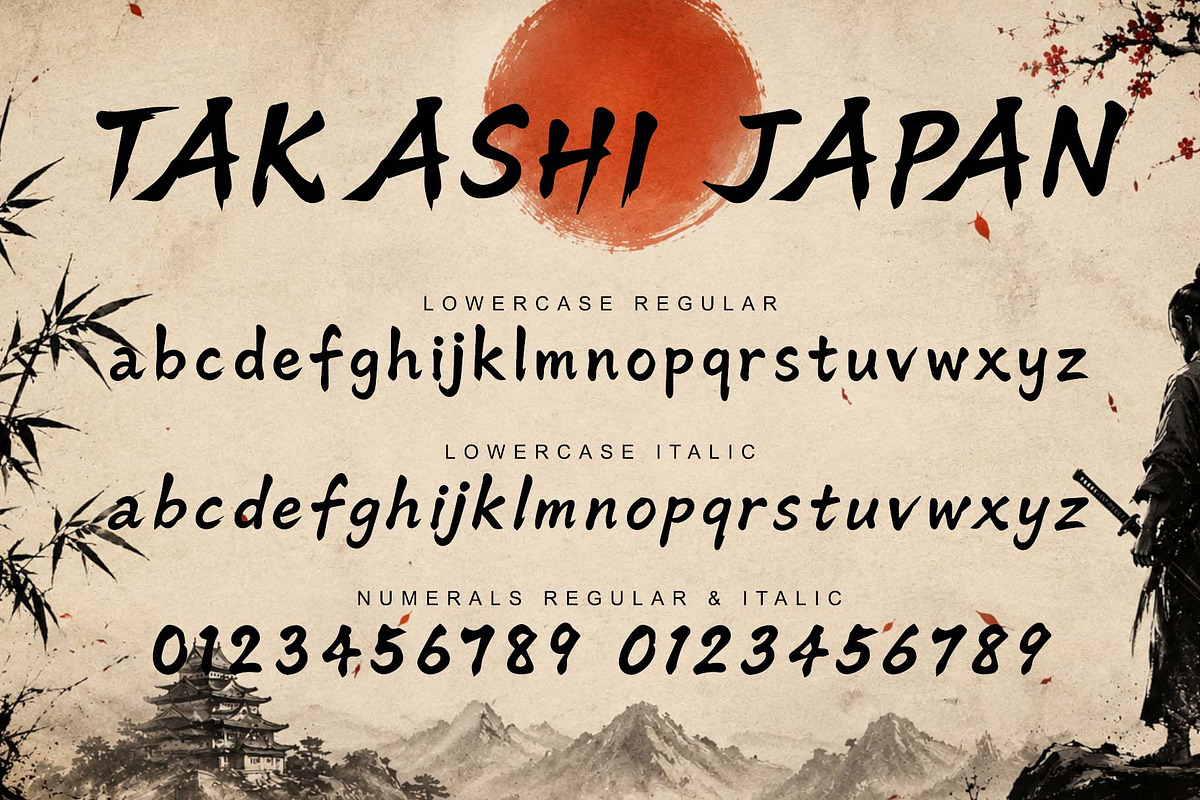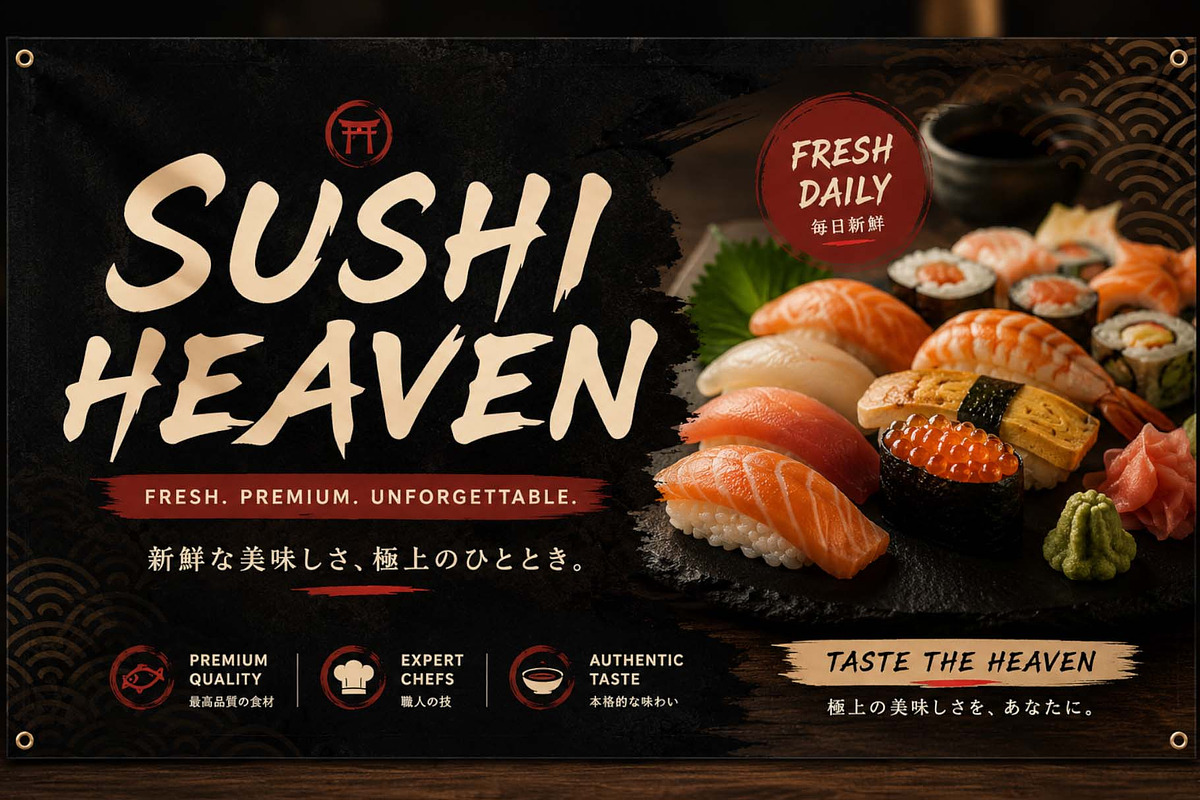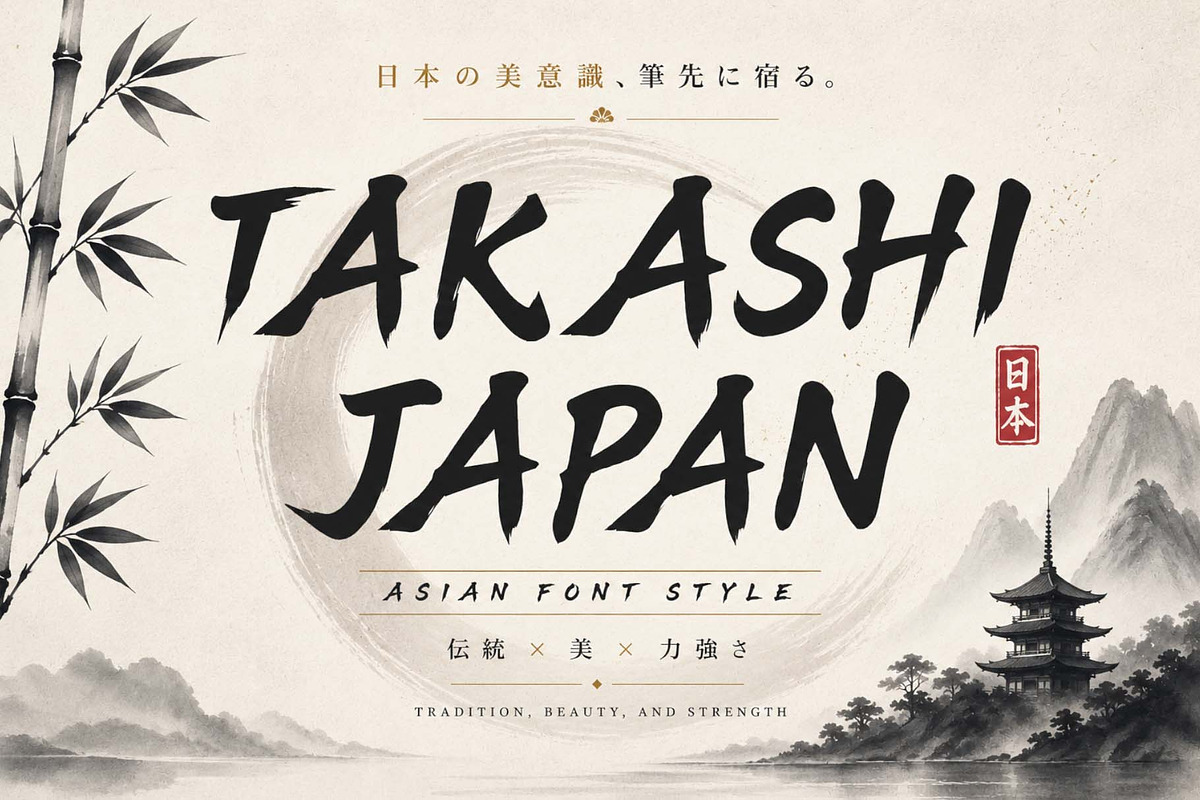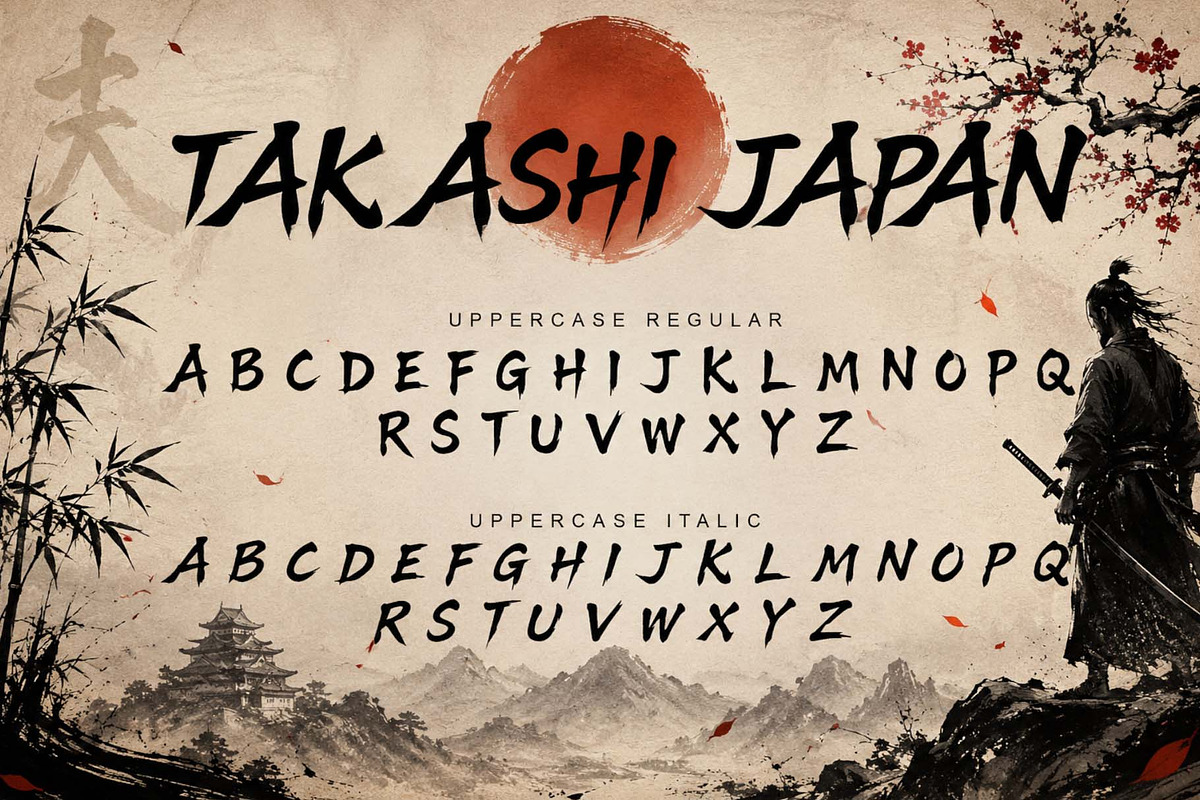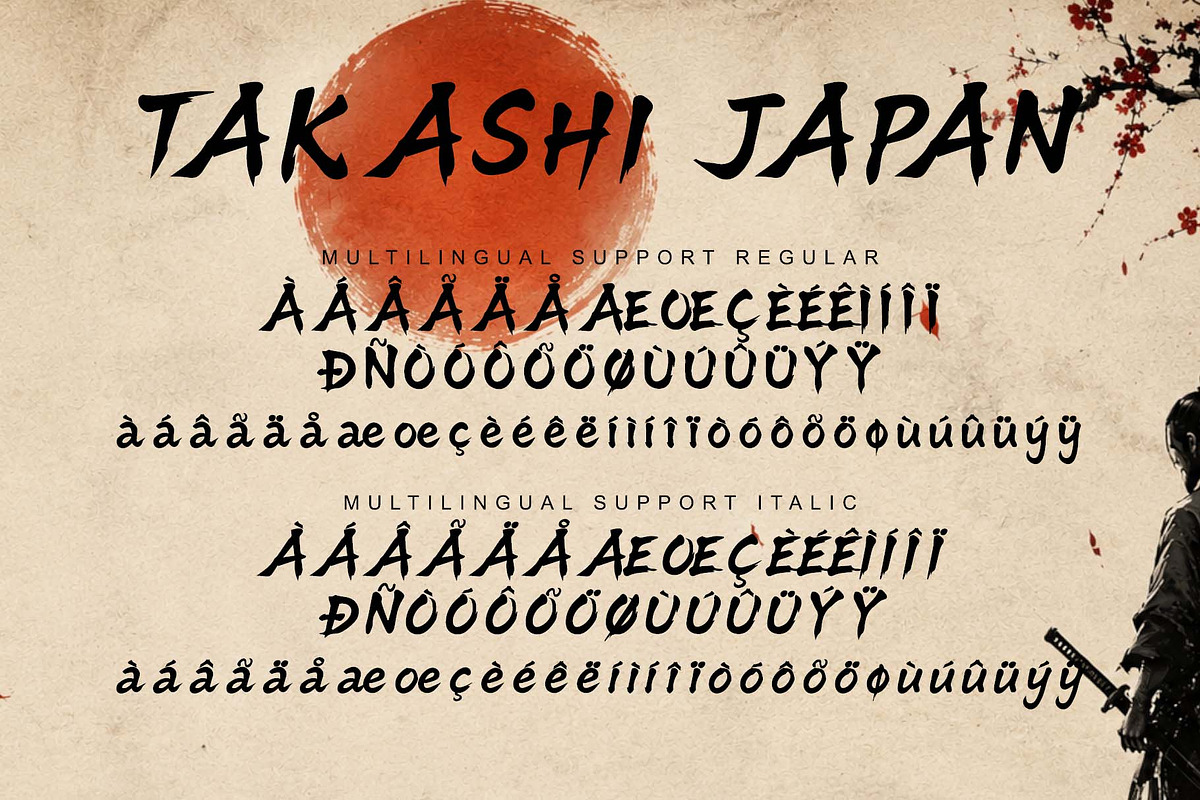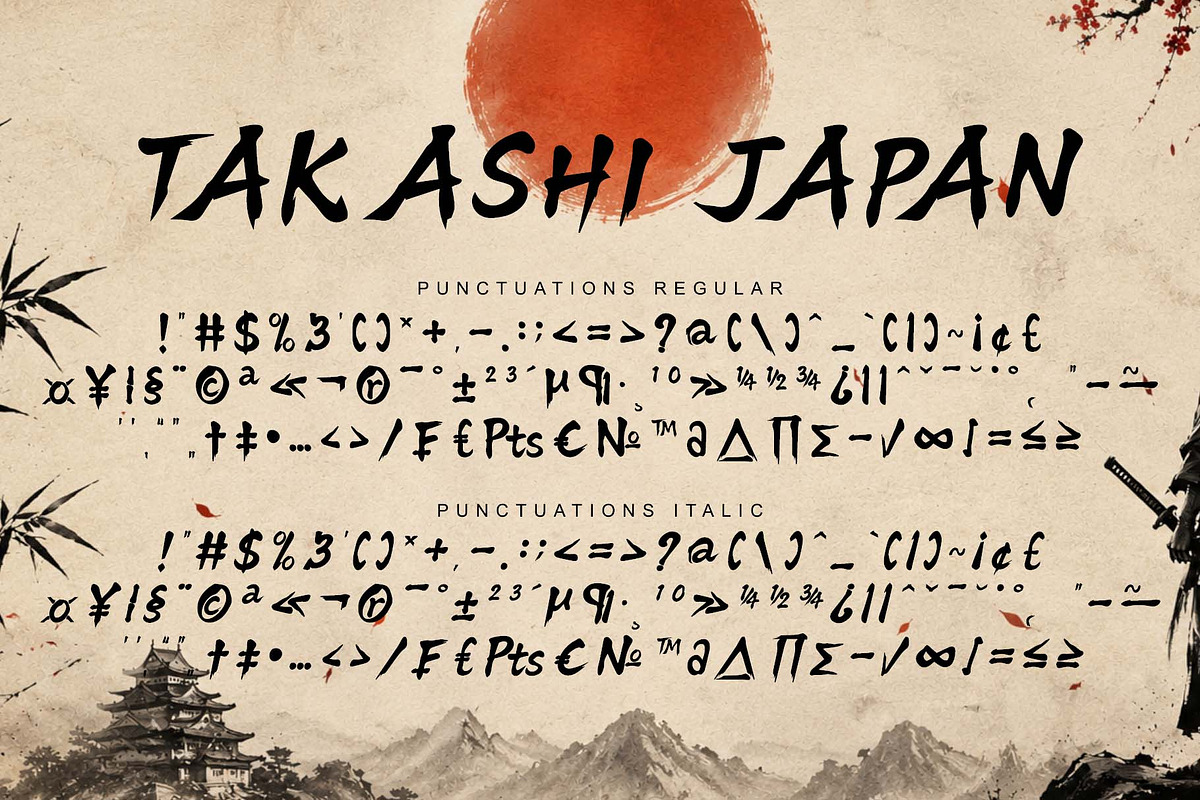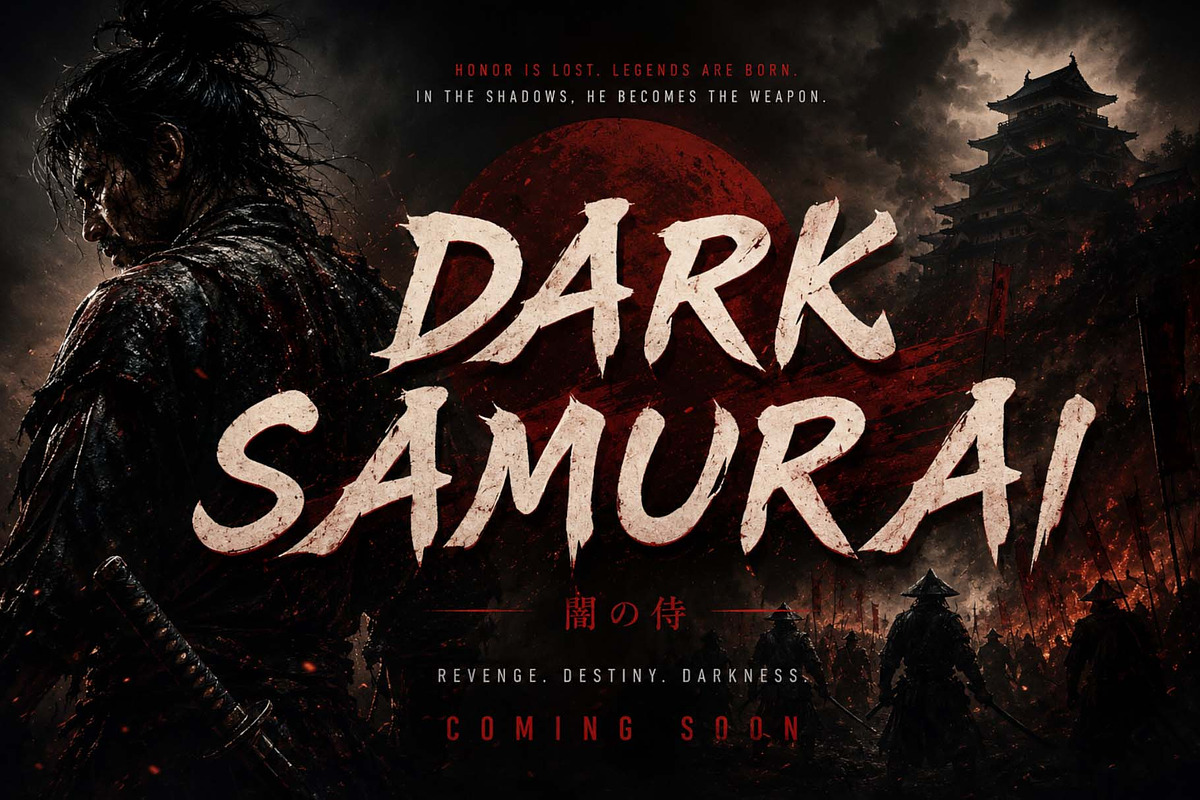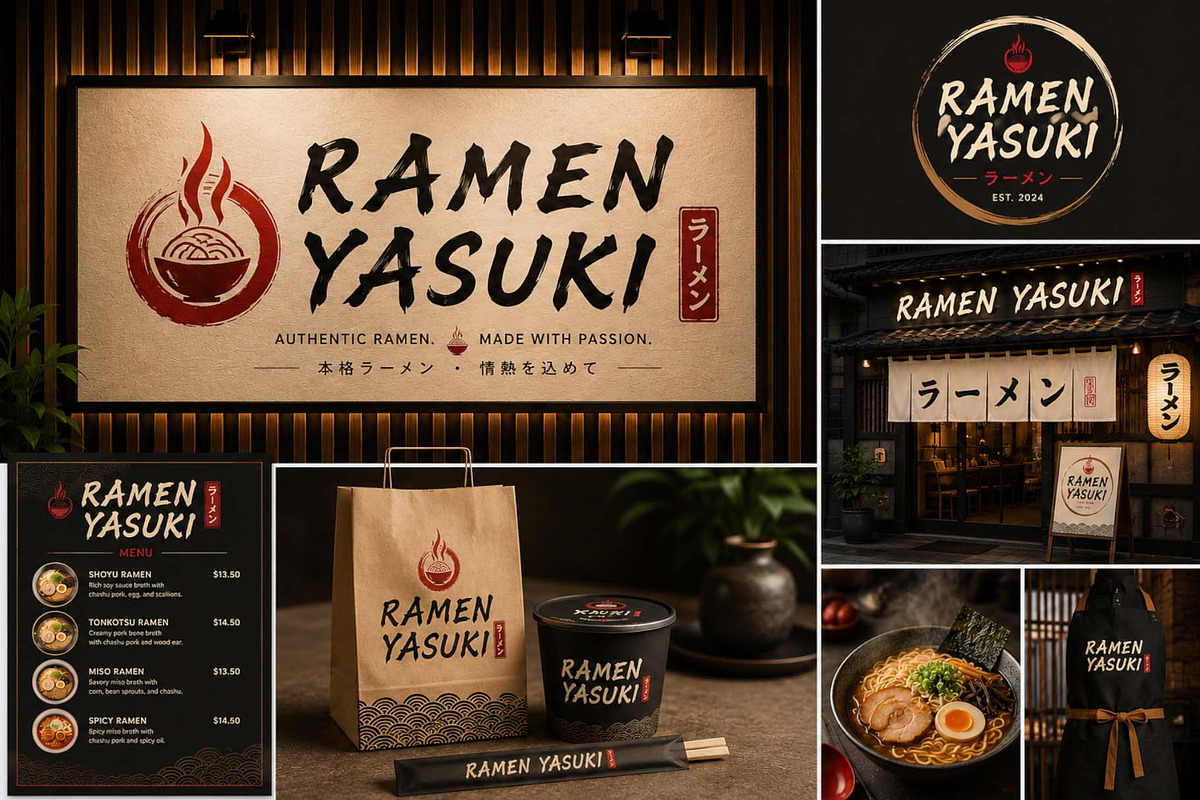
Takashi Japan
Takashi Japan adalah font display bergaya kuas Jepang (Japanese brush font) yang terinspirasi dari seni kaligrafi tradisional samurai. Setiap karakter memiliki sapuan kuas yang tegas, dinamis, dan penuh energi, menciptakan kesan kuat, berani, serta autentik. Cocok digunakan untuk desain bertema Jepang, samurai, ninja, anime, game, poster film, branding restoran Asia, merchandise, hingga konten budaya oriental. Dengan karakter yang unik dan mudah dikenali, Takashi Japan menghadirkan perpaduan sempurna antara tradisi, kekuatan, dan estetika modern.